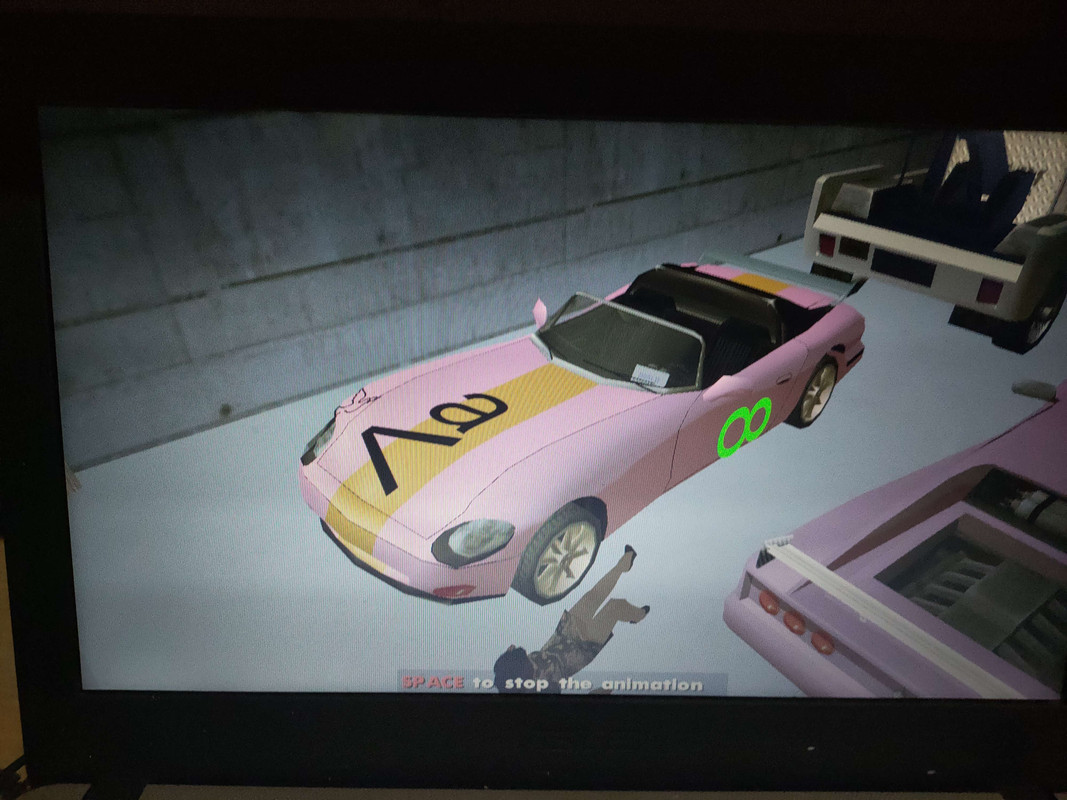
$XieXie$ Posted March 7, 2023 Apakah ada font persegi panjang? Soalnya Diwebdings ga ada persegi panjang soalnya saya ingin membuat lampu rem turismo tapi bingung menggunakan apa
1 $Dullboy$ Posted March 7, 2023 Dikreasikan kan mas itu kan huruf "g" webdings kan persegi, nah biar jadi persegi panjang masnya buat "ggg" gitu. 1
0 $XieXie$ Posted March 7, 2023 Author Posted March 7, 2023 8 minutes ago, Cheesecake said: Dikreasikan kan mas itu kan huruf "g" webdings kan persegi, nah biar jadi persegi panjang masnya buat "ggg" gitu sudah buat seperti itu tapi hurunya ga gabung alias ada spasi
0 $Dullboy$ Posted March 7, 2023 5 minutes ago, ReXie said: sudah buat seperti itu tapi hurunya ga gabung alias ada spasi saya buat nyatu ga ada spasi itu udah yakin "ggg" atau "g g g"?
0 $bhadoeet98$ Posted March 7, 2023 Coba di wingdings , wingdings 2 dan wingdings 3 soalnya saya udah coba dari web dafont di orang lain ga sama kaya di visu kita nanti jadi nya angka angka doang atau huruf doang. Cuma support webdings sama wingdings Contohnya sperti ini setelah saya pake font custom dari link dafont Spoiler [img\] Jadi di visu teman Kan berbed hanya support webdings dan wingdings
Apakah ada font persegi panjang? Soalnya Diwebdings ga ada persegi panjang
soalnya saya ingin membuat lampu rem turismo tapi bingung menggunakan apa